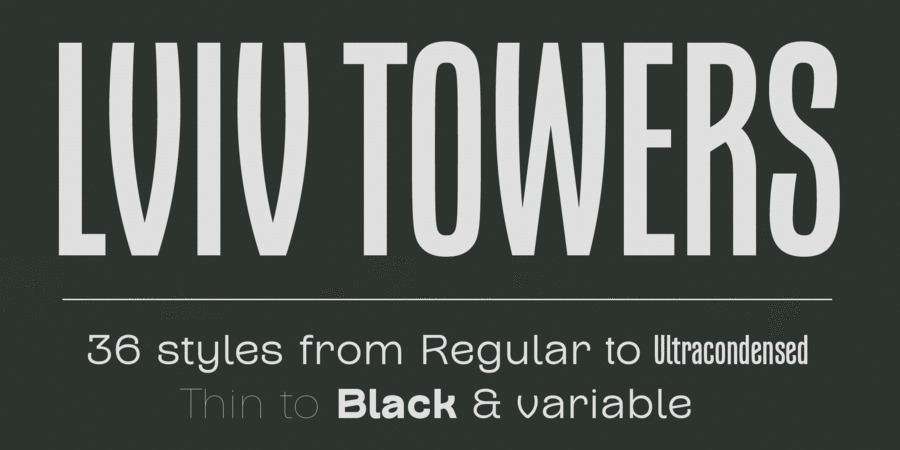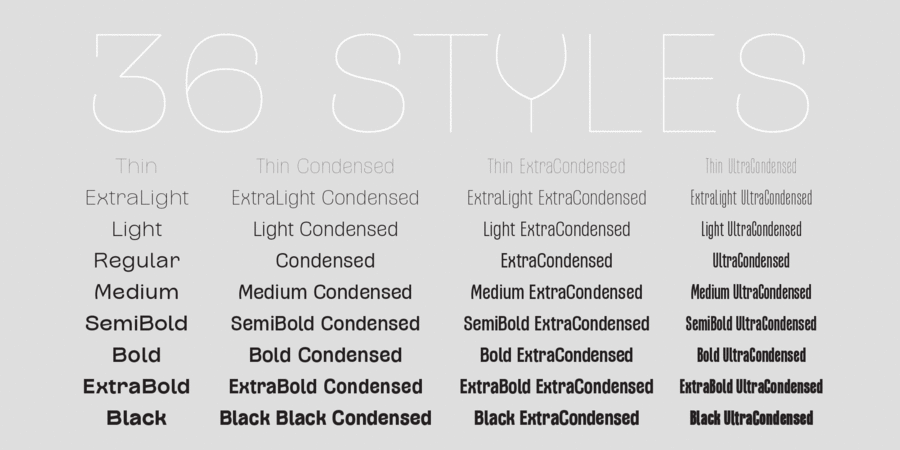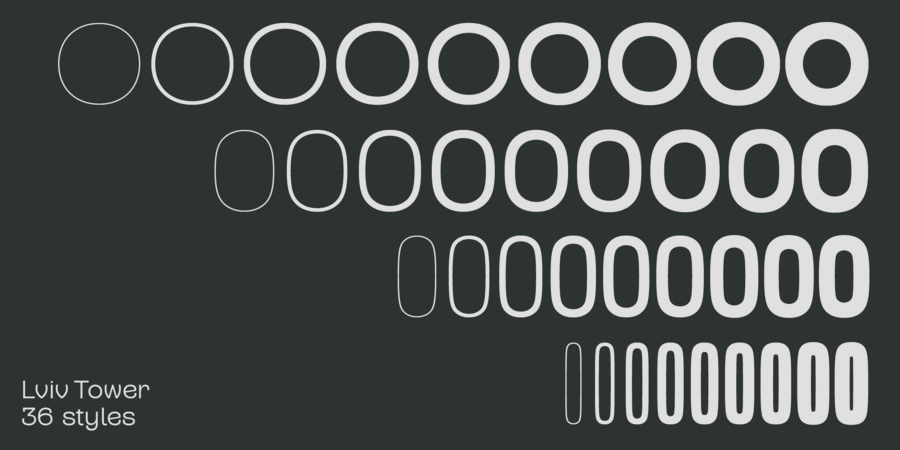
Lviv Towers (37 шрифтів)
Цей гротескний шрифт із неперевершеною індивідуальністю і харизмою. На ідеї його створення вплинули старі написи магазинів у Львові та театральні постери 19-го століття. Шрифт чудово підходить для вишуканого продукту з багатим смаком і незабутнім ароматом. Шрифт розробили Віктор Федюк і Кирило Ткачов у 2024 році.
Асоціації з сімейством шрифтів Lviv TowersОсобистість і характер гарнітури:
міський, якісний, комфортний, гладенький, гнучкий, оригінальний, добрий, приємний, консервативний, старомодний, художній, красивий, історичний, пластичний, динамічний, витончений, делікатний, естетичний, тонкий, легкий, ясний, чистий, невагомий, прозорий, крихкий, дротяний, культурний, багатий, ніжний, затишний, неоновий, інтимний, скляний, ремісничий, впевнений, важливий, переконливий, дерев'яний, сильний, помітний, рівний, стрункий, худий, стиснений, високий, самобутній, характерний, цікавий, чіткий, стійкий, кінематографічний, твердий, гучний, авторитетний, наполегливий, надійний, яскравий, важкий, потужний, тісний, чорний
Місто, екологія, одяг, вода, сувенір, туризм, історія, музей, мистецтво, архітектура, інтер'єр, косметика, парфумерія, театр, кава, скульптура, дієта, краса, туалетна вода, АСМР, лосьйон, мода, надгробок, пам'ятник, меморіал, Трофей, нагорода, меблі, ремесло, дерево, наліпка, кафе, хліб, кіно, кінотеатр, торгівля, прем'єра, хмарочос Гарнітура має ознаки стилів: